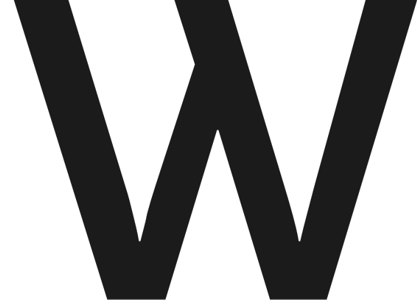
Nein, nicht die Scala. Die gesuchte Schrift kennt keine Varianten mit Serifen.
Die gesuchte Schrift ist noch recht jung und heißt weder Lux noch Base. Hier das komplette w:
Genau, bravo!
TYPOGRAFSKI, übernehmen Sie!